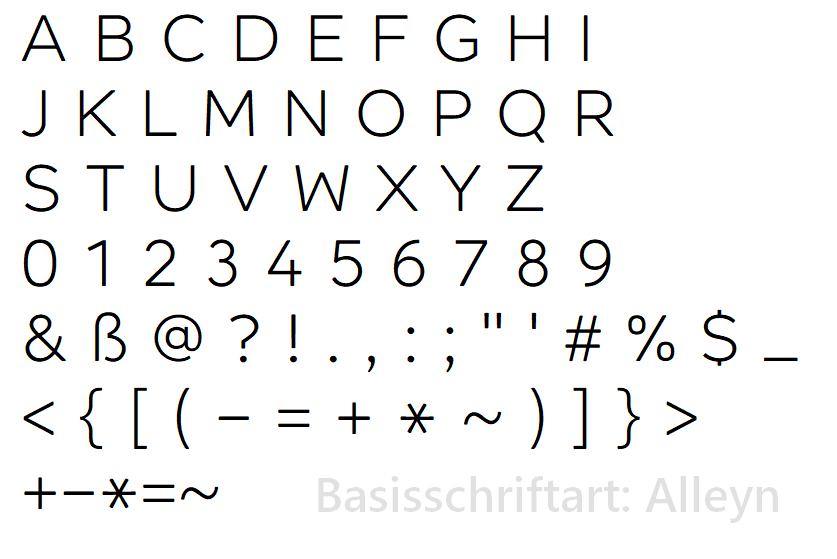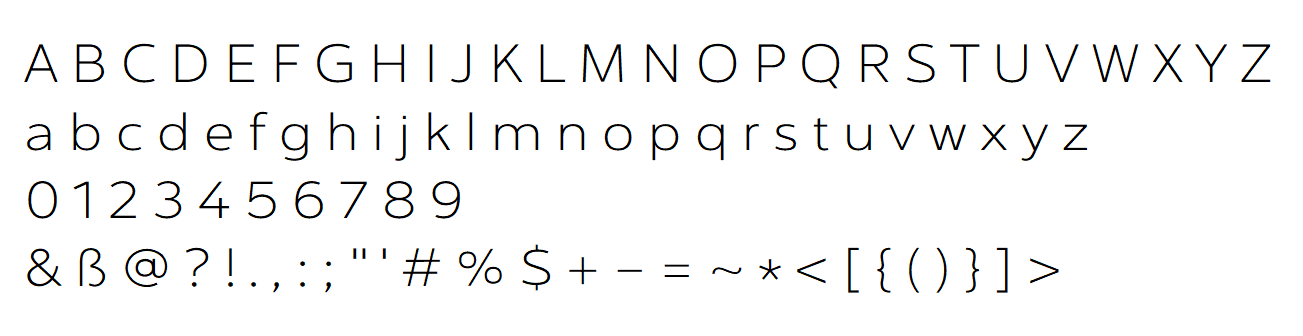
Brauche neutralen Font, aber in wide/extended?
Hallo! Ich brauche für eine Tastatur einen neutralen Font in "wide" (sagt man "breit" auf Deutsch?). Je mehr ich vergleichend suche, desto großartiger finde ich die Noto Sans, Segoe UI, oder auch die Open Sans. Alle diese empfinde ich als perfekt mit einer kleinen Ausnahme: ich brauche den Font in wide/extended, d. h. die Glyphen sollen breiter sein, nicht nur ein bißchen, sondern schon eine ganze Ecke. Leider finde ich wirklich nichts. Hat jemand einen Tipp?
Habe hier mal ein Bild wie ich mir das vorstelle. Das ist ein extended Font, den ich in Richtung Open Sans händisch zurechtgebogen habe, eine Pfuscherei nur zur Anmutung:
Danke für die Vorschläge, jetzt weiss ich schonmal, daß ich bisher nicht so falsch lag. Denn die Montserrat hatte ich schon im Auge, und hatte sogar schon Hand an sie angelegt, denn einige Glyphen von ihr sind etwas auffällig J G Q 7 1 3. Im Großen und Ganzen ist sie aber schon ein super Kandidat. Übrigens, nach stundenlangen Schrift-Vergleichen bemerke ich, daß es vor allem immer dieselben Glyphen sind, die am ehesten aus dem Rahmen fallen bzw. sich deutlich unterscheiden in der Gruppe der Segoe-ähnlichen, nämlich: & ß @ ? J G Q R K 1 3 6 9. Natürlich ist alles Geschmackssache, aber ich empfinde bspw. ein "G" ohne Horizontalbalken ziemlich strange. Ebenso ein "K" mit Horizontalbrücke:
Bzgl. des G gibt es mindestens zwei Varianten mit geänderten G. Argentum Sans und Gontserrat.
In der Truneo sind einige andere Lettern geändert:
Notfalls kannst Du Dir Deine eigene Bastelversion bauen?
Sample.png.eee2c9d0b5c8611ebbba8e2343b9fc49.pngDanke für den Hinweis, Uwe. Ja, meine Bastelversion (auf Basis der Interval Next Wide) ist schon weit fortgeschritten. Hatte anfangs ein schlechtes Gefühl als Pfuscher Hand anzulegen an die "meisterhaften" Glyphen, bis ich bemerkt habe, daß es umgekehrt ist, und ich der Perfektionist bin, der fahrlässig gestaltete Glyphen schematisch korrigiert. Zum Beispiel finde ich bei professionell gestalteten Schriften oft uneinheitliche Strichstärken, da hat wohl jemand schnell mal "scale down" gemacht, und die Strichstärke wurde ebenfalls verkleinert. Sowas empfinde ich als Pfuscherei. Außerdem sehe ich bei vielen "wide" Schriftschnitten die Glyphen einfach nur in die Breite gezogen mit entsprechender Strichstärken-Verzerrung. Wirklich von Grund auf neuzeichnen macht wohl auch nicht jeder? Verzerren kann jeder Laie auf Knopfdruck.
Empfindet Ihr in dieser Schriftübersicht irgendeine Glyphe als auffällig ausfällig? Außer dem vertikal zentrierten Asterisk, das ist zweckbedingt, da die Schriftart auf Tastenkappen kommt. Aber sonst?
Hier noch was fürs Gruselkabinett:AdelleSansEXT-Thin.png.bbae588506dbdcb29a7f0e2ce2fa44fe.png
S, s, ß, e, a und $ wirken irgendwie noch unausgegoren auf mich.
Wäre es nicht einfacher auf einen Schnitt eines ausgefeilten Klassikers wie der oben verlinkten Myriad zu setzen? Dass da »gepfuscht« wurde, bezweifle ich jetzt einfach mal. Wenn Du ein CC-Abo hast, fallen nicht mal weitere Kosten an. 🤷🏼‍♂️
Jetzt, wo Du es sagst sehe ich es auch, daß der Mittelteil des "S" und "s" und "$" zu linear verläuft und gewundener sein sollte. Die Minuskeln sind leider insgesamt ziemlich unelegant, das ist mir auch schon aufgefallen. Was ist an dem Eszett auffällig?
Die Myriad schaue ich mir mal an.
Eine Frage noch zum Thema Pfusch. Was wäre wenn man einen makellos gestalteten Font nimmt, und daraus eine "wide" Version macht, indem man dessen Glyphen in die Breite zieht, und die dabei als Nebenwirkung auftretende Horizontal-Verzerrung der Strichstärke wieder entzerrt, indem man die Outlines horizontal wieder ausdünnt. Bleibt da noch irgendeine Verzerrung übrig? Sollte eigentlich nicht, oder?
Zum Beispiel finde ich bei professionell gestalteten Schriften oft uneinheitliche Strichstärken, da hat wohl jemand schnell mal "scale down" gemacht, und die Strichstärke wurde ebenfalls verkleinert.
Steile These. Gibt es für diese Behauptung auch anschauliche Beispiele?
So steil, daß nichtmal ein Fussball drauf wegrollt. Man findet das eigentlich fast überall, vor allem bei "@", wo der Kringel nur selten die Strichstärke hat, die im Font standard ist. Oder auch auffällig hier im Font "Programme", wo das Copyright-Zeichen einfach durch "scale-down" des kleinen "c" enstanden ist.
vor 12 Stunden schrieb Laptop:
Man findet das eigentlich fast überall, vor allem bei "@", wo der Kringel nur selten die Strichstärke hat, die im Font standard ist.
Dass in einer Schrift die Strichstärke wechselt, ist in erster Linie der Optik geschuldet.
Z. B.: Waagrechte Linien sind mitunter dünner als senkrechte Linien.
Der Kringel beim @ ist meistens ein feinerer Strich, als bei den anderen Buchstaben usw.
Ebenso sind bei vielen Schriften auch die Linien der Minuskel etwas feiner als die der Versalien, die Linien der runden Formen fetter als die der geraden Formen usw.
Es liegt im Ermessen des Schriftentwerfers, wie er das handhabt. Es gibt eher wenige Schriften mit "einheitlicher Linienstärke". Eine messbare „Standardstrichstärke“ findet man in einer optisch ausgewogenen Schrift kaum.
vor 16 Stunden schrieb Laptop:
So steil, daß nichtmal ein Fussball drauf wegrollt. Man findet das eigentlich fast überall, vor allem bei "@", wo der Kringel nur selten die Strichstärke hat, die im Font standard ist. Oder auch auffällig hier im Font "Programme", wo das Copyright-Zeichen einfach durch "scale-down" des kleinen "c" enstanden ist.
Ich habe schon lange nichts mehr gemacht in dem Bereich, aber Ikarus M, Fontographer und Fontlab Studio sind die, mit denen ich ein bisschen Erfahrung habe.